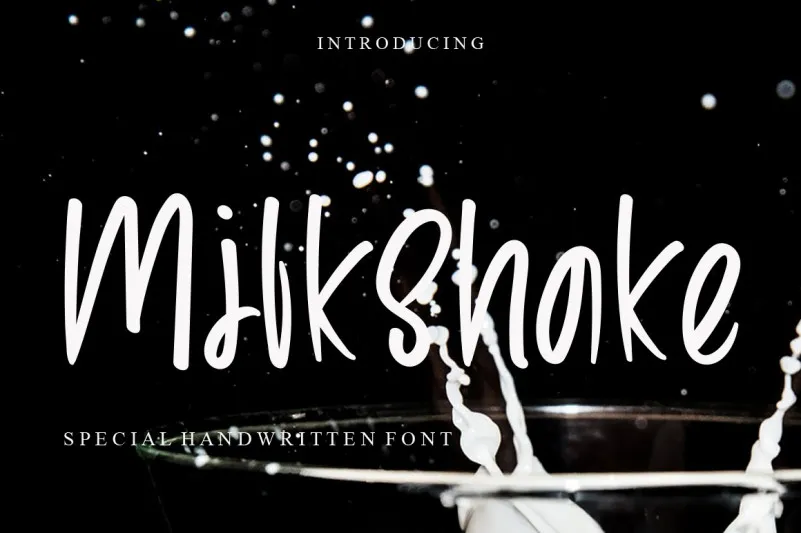
Esta fonte “Milkshake Font” é uma escolha perfeita para quem busca algo simples e confortável no seu trabalho. Ela tem um tom elegante e desenho cívrico, sem perder a personalidade autêntica de uma escrita à mão real. Perfeito para projetos criativos onde você deseja transmitir um toque familiar ou casual, desta fonte é possível criar algo que pareça fora deste mundo. Se apaixone por esta fonte e use-a em seus trabalhos mais ousados e inovadores!